世界上的语言种类这么多,我们除了日常的口语交流之外,也还是会用到书面表达的。书面表达就需要手写字体了,我们一起来看一下下面这几款手写字体,是否有吸引到你的注意
谌利军冠军手书这款字,笔锋沉稳,霸气,体现了属于体重冠军的独有力量。该字体适用于杂志、书刊,品牌广告和产品包装设计,以及社交网络的个性化用字。
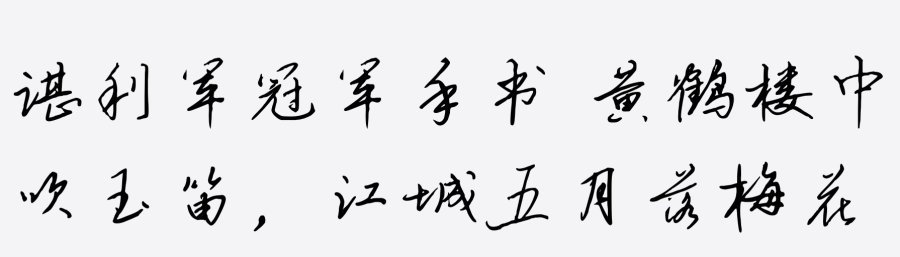
焦金流石这款字体笔画流畅飘逸,结体内紧外松,开合对比强烈,有比较强的视觉感染力。适用于现代诗歌、短文的排版,以及文化、商业类品牌的广告语设计。
年年有余字体是一款可商用的硬笔手写,具有古典、有力、优雅、简约 的风格,可以满足您设计上的需求。